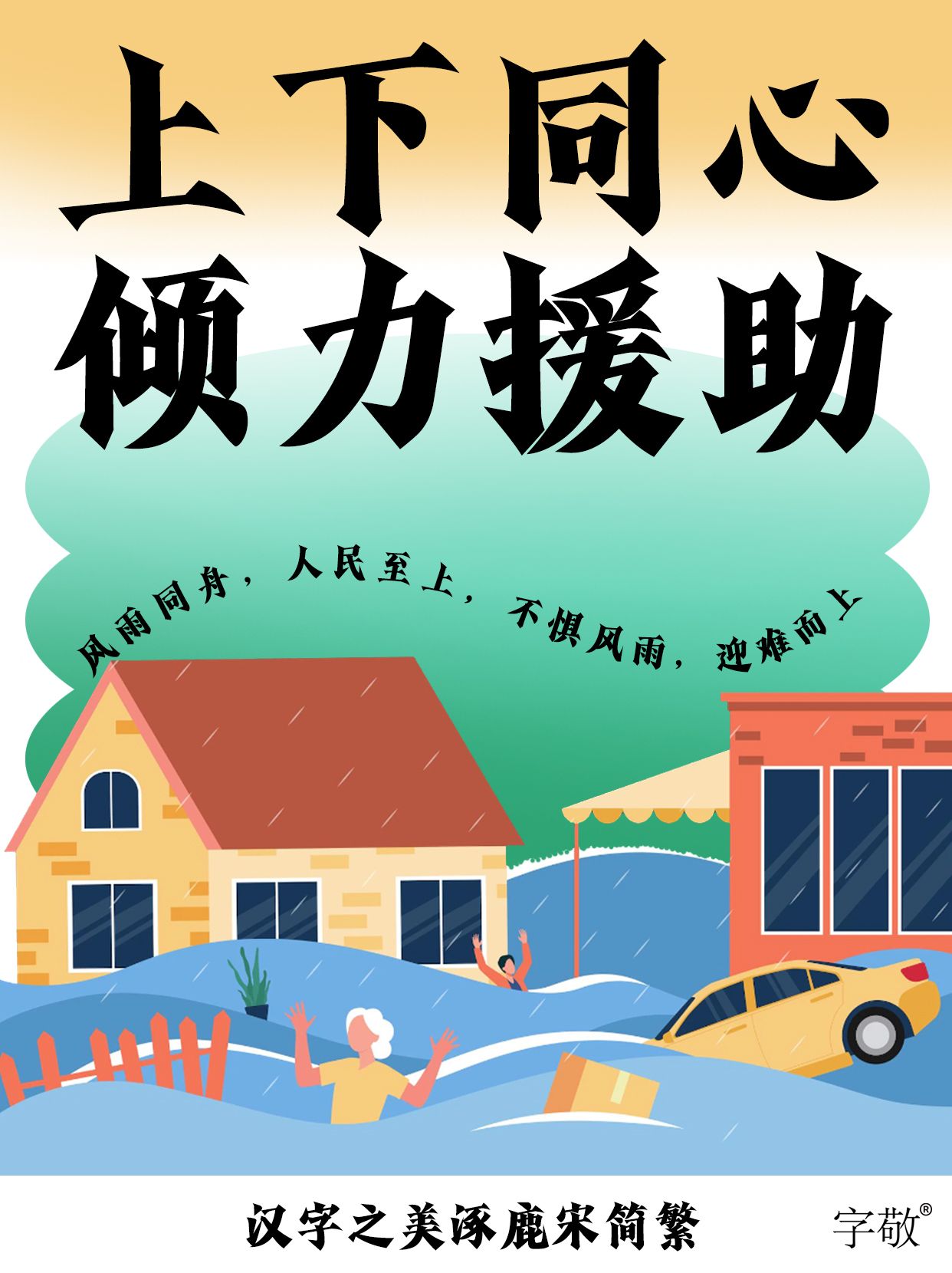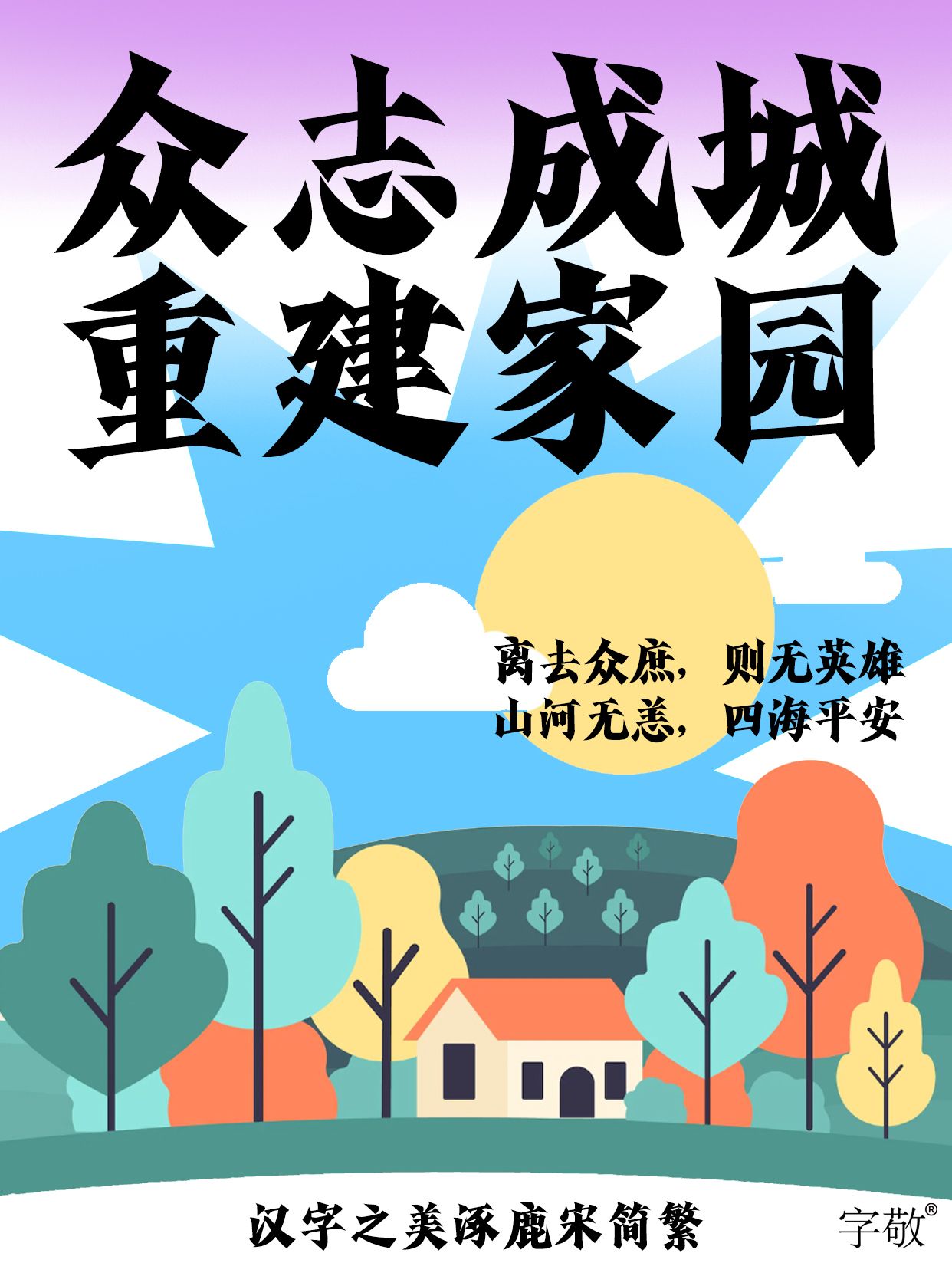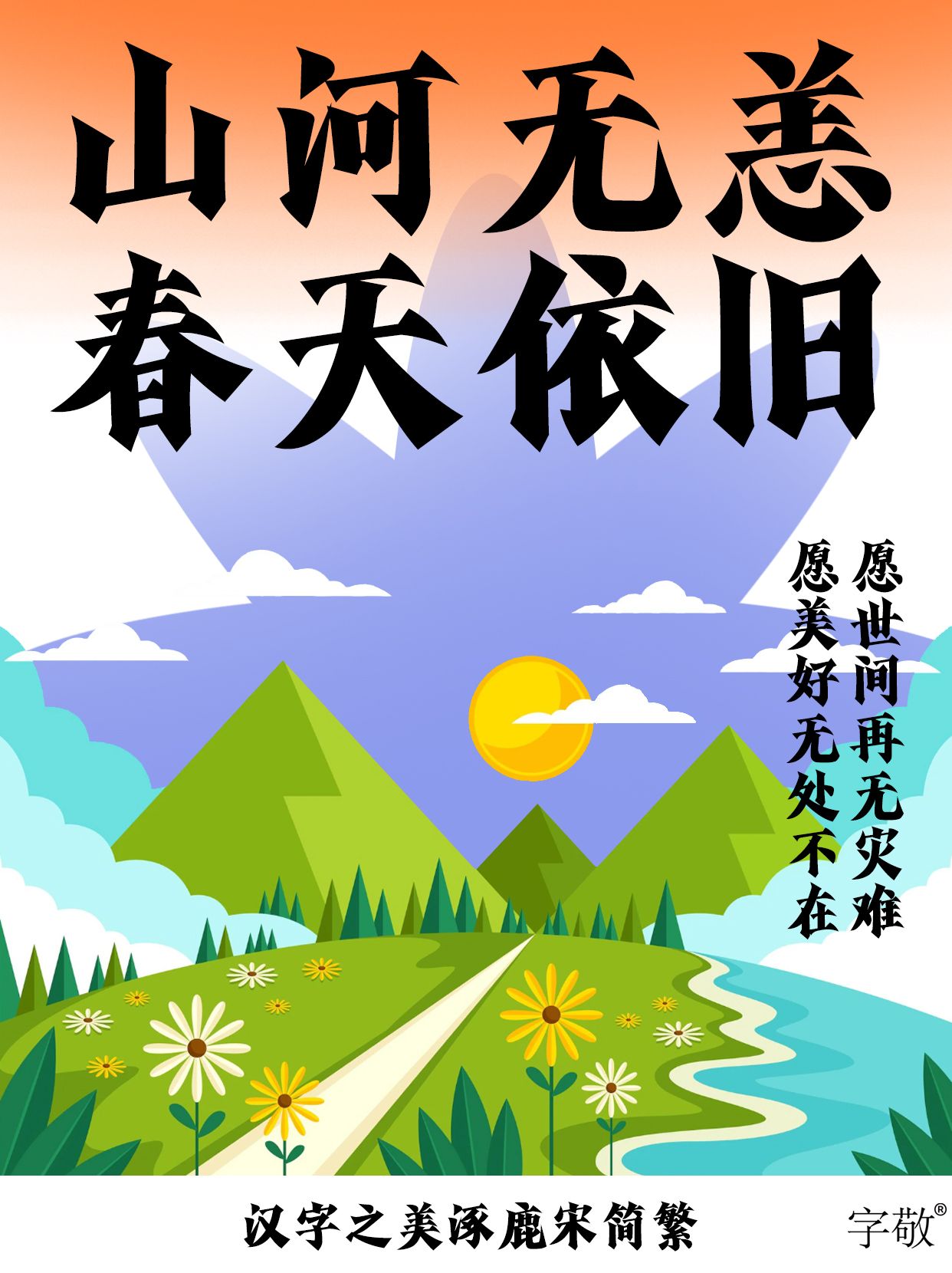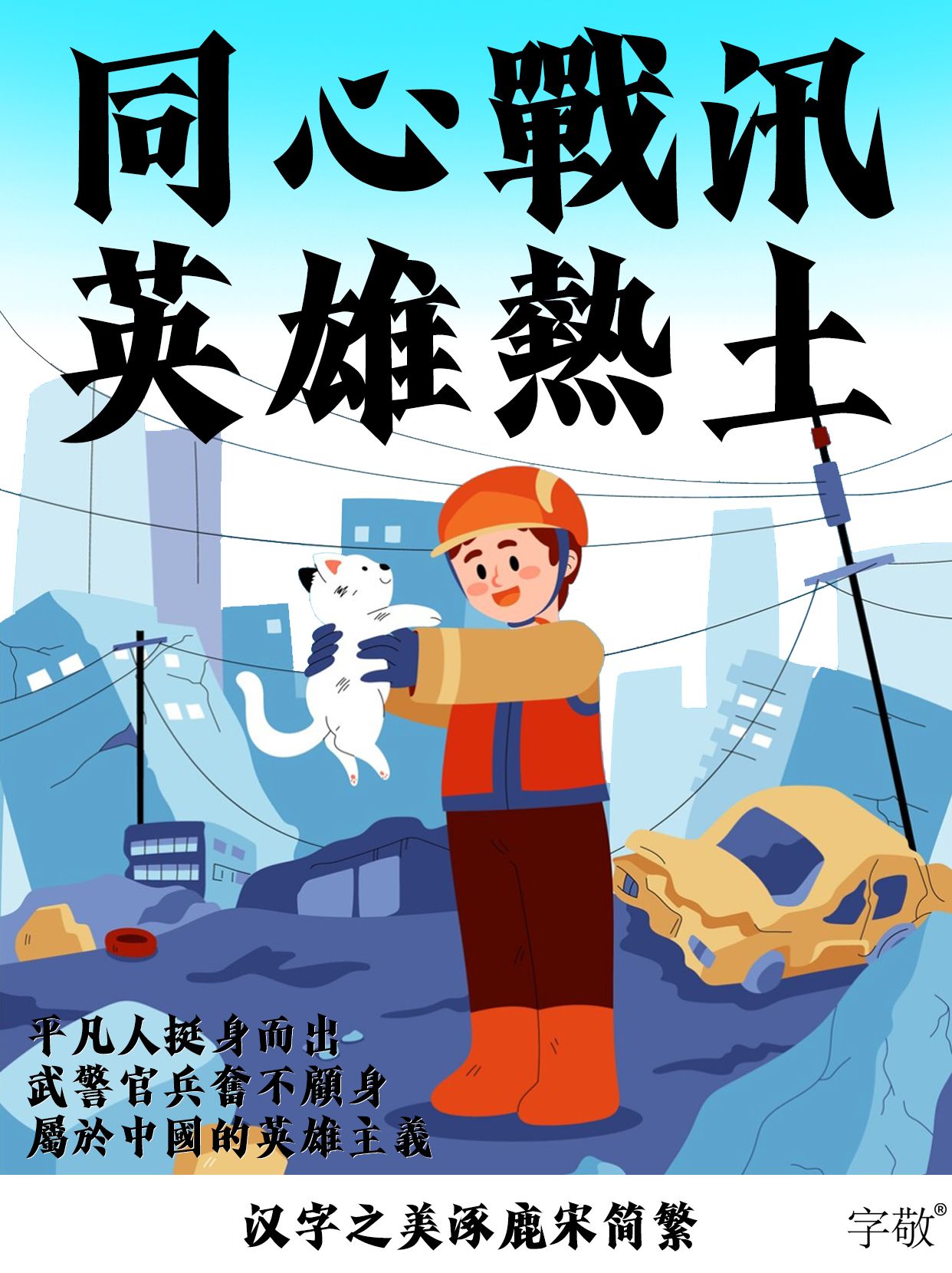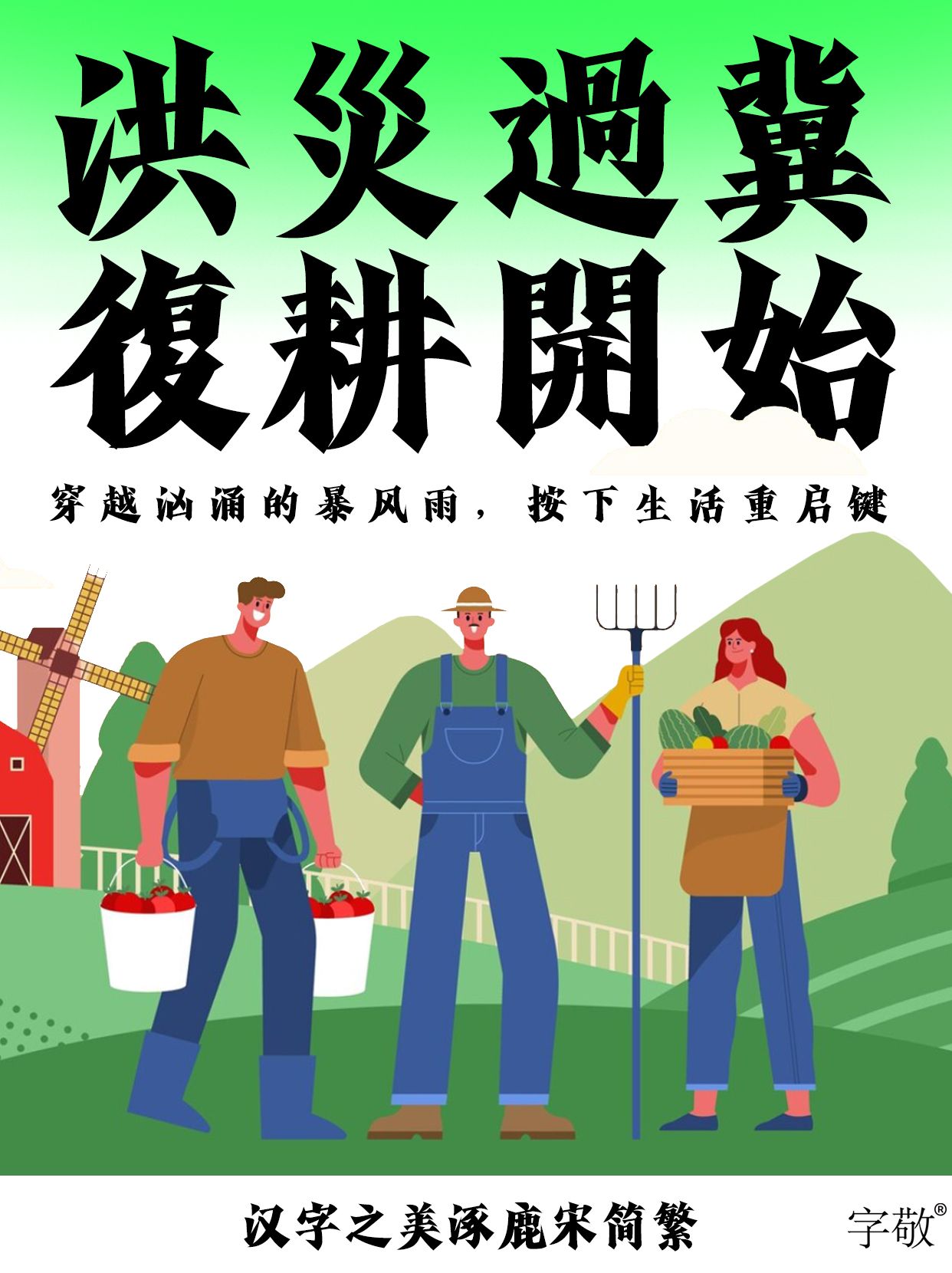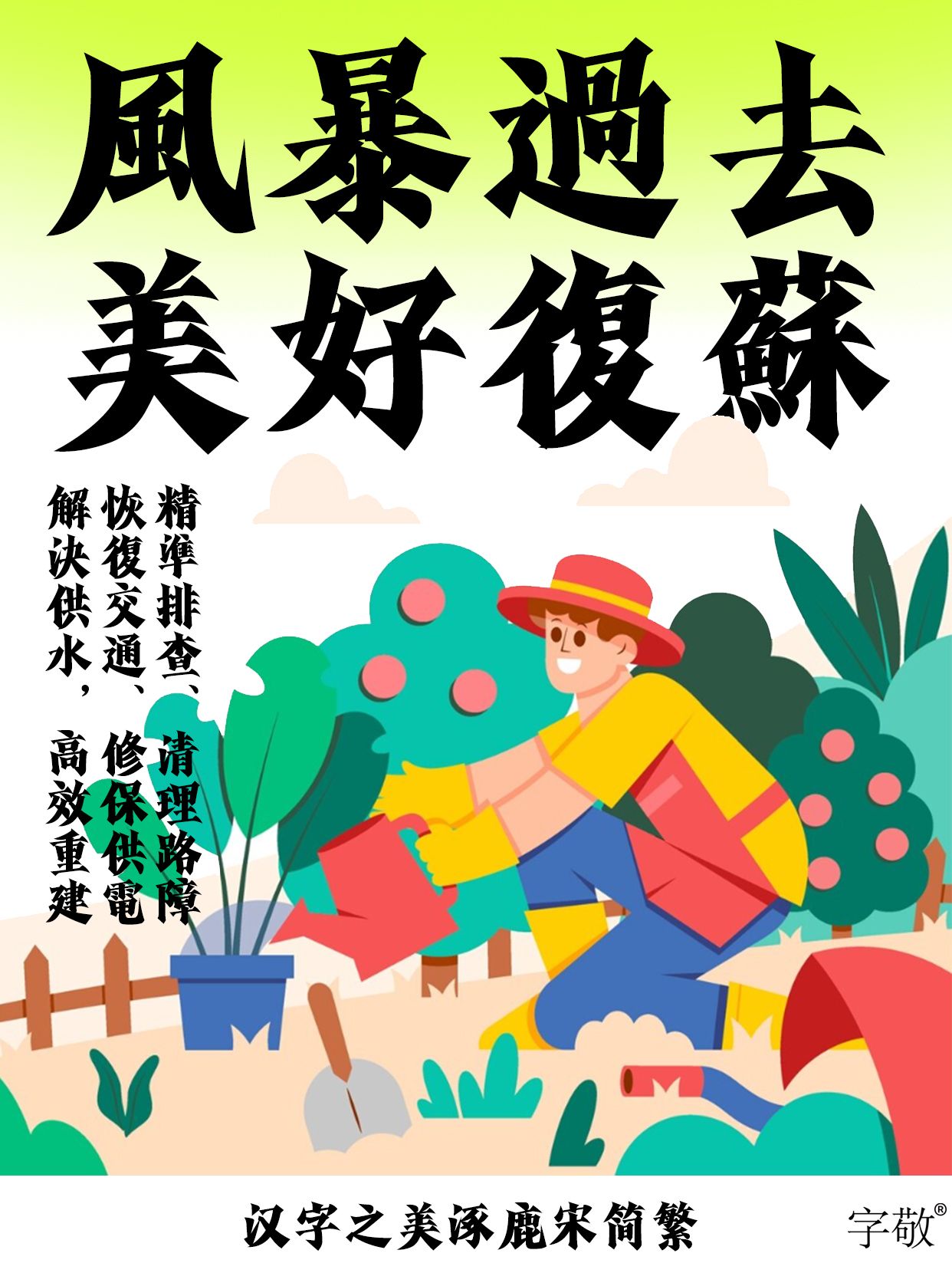
汉字之美涿鹿简繁 | 字敬华夏,以字传情,定向免费字体助力河北复耕,重建美好家园!
“千古文明开涿鹿”,一场名垂青史的涿鹿之战,让其成为中华第一古战场,自此中原收复,华夏统一,历史之轮开启了新的转动。
时隔千年,这片中原土地,涓滴之力在此汇聚成洋。暴雨席卷,洪水围困,涿鹿、涿州等中原地区均受到不同程度灾害损失。全国人民星夜驰援,和衷共济,重建家园,团结一致的华夏精神永不缺席。
【汉字之美涿鹿宋简繁】
字体类型:宋体
字体风格:国风、力量
字 符 数:10561
设 计 师:郭仕豪
应用场景:标题、内文、海报、logo、包装
字体描述:用墨浓厚,结构中正规整,起收笔、转折等特点明显、夸张统一